2023 年のベストセリフフォント 36 (無料およびプレミアム)
公開: 2023-05-23あなたは、デザイン プロジェクトを向上させる完璧なセリフ フォントをお探しのグラフィック デザイナーですか? それとも、最高のセリフ フォントが何なのか知りたいだけですか? さあ、もう探す必要はありません。
この記事では、利用可能な最高のセリフ フォント 36 個を紹介します。 Times New Roman や Garamond などのクラシックなフォントから、Georgia や Baskerville などのモダンなお気に入りまで、あらゆるフォントを取り揃えています。 各フォントには、プロジェクトに適切なフォントを選択するのに役立ついくつかの興味深い事実と統計が付属しています。
Web サイトのデザイン、ロゴの作成、印刷プロジェクトに取り組んでいる場合、または Adobe の Serif フォントを検討している場合でも、この記事を読み進めて、作品に優雅さと洗練さを加える最高の Serif フォントを見つけてください。
最高のプレミアムセリフフォント
デザインプロジェクトを向上させるための完璧なプレミアムセリフフォントをお探しですか? 2023 年のトップ ピックをご覧ください。次のプロジェクトに最適なオプションを見つけることをお見逃しなく – 引き続き読み続けて、推奨事項を確認してください。
ラ・ドルチェ
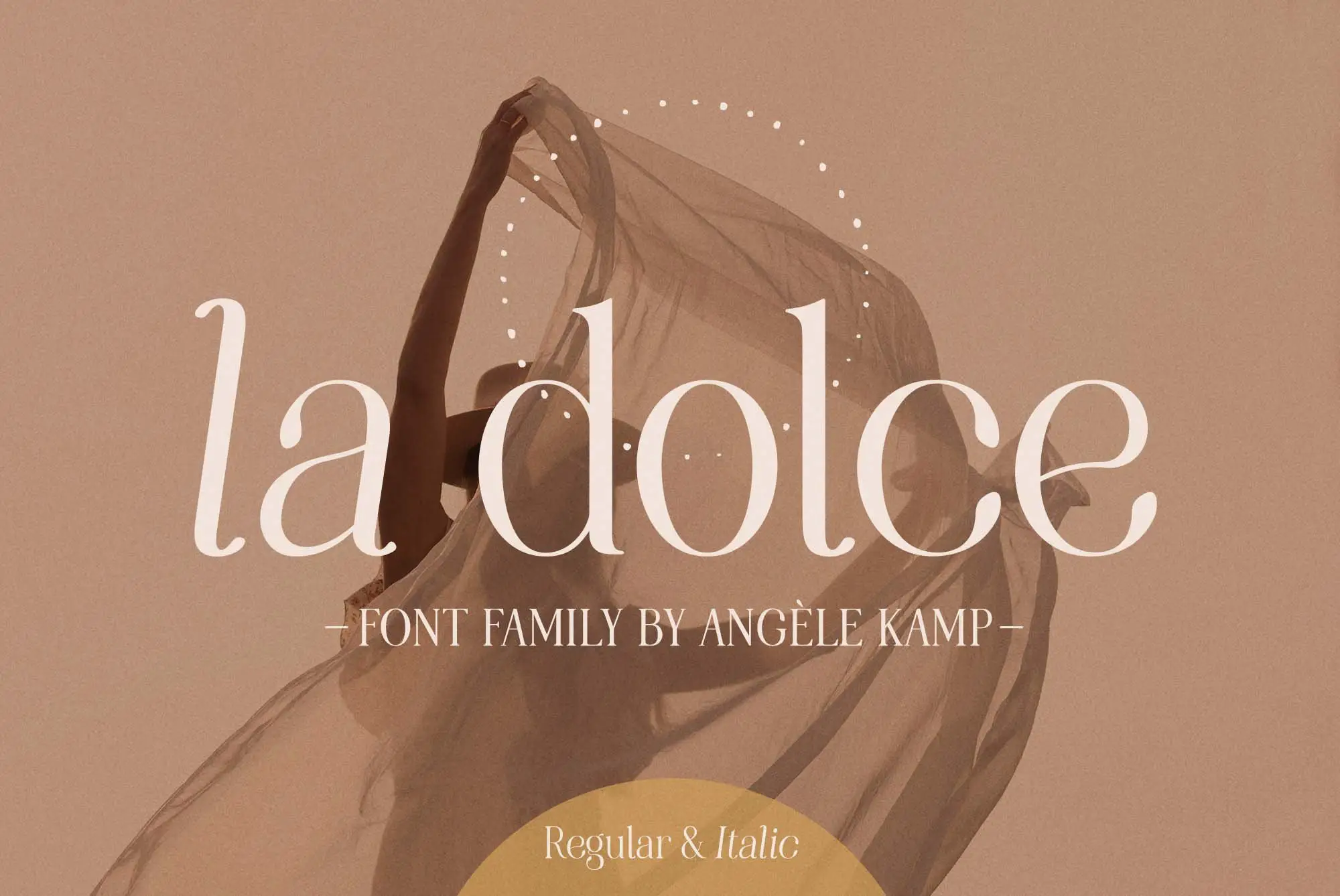
La Dolce は、フェミニンな雰囲気を醸し出す洗練されたセリフ フォント ファミリーです。 優雅さとスタイルを必要とするあらゆるデザインプロジェクトに最適です。
このフォント コレクションには、太字、標準、斜体、太字斜体を含む 4 つの異なるスタイルが含まれており、多用途性と機能性を備えています。
精緻なディテールとエレガントなスタイルが印象的です。 Google Serif フォントは人気の検索語であるため、このフォント ファミリはコレクションに追加するのに最適で、検索結果で目立つユニークなデザインを作成するのに役立ちます。
レイジェンシー
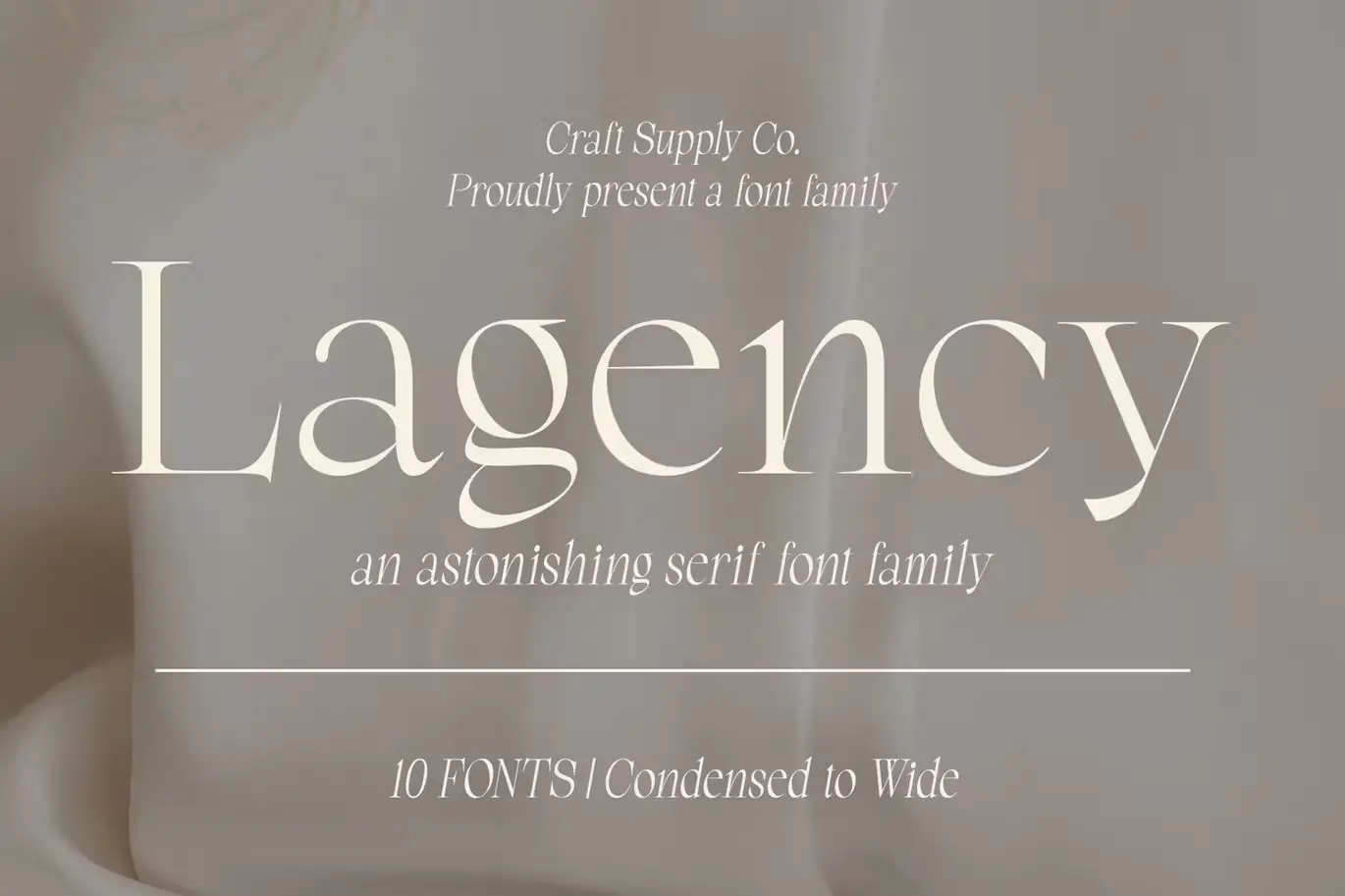
Lagency は多用途で美しいセリフ フォントで、凝縮からワイドまで 10 種類のスタイルがあります。 印刷物、Web、ロゴデザインなど、さまざまな用途に最適です。 フォントの柔軟性の必要性を理解しているグラフィック デザイナーが、愛情を込めて Lagency をデザインしました。
モダンな Serif フォントのきれいな線と印象的なタイポグラフィーは、印刷または Web プロジェクトでの使用に最適です。 大画面でも読みやすい書体を探している場合でも、ロゴやその他のグラフィックスに個性を加える特別なものが必要な場合でも、Lagency は最適な選択肢です。
Lagency では太字フォントが利用できるため、すべてのアプリケーションで独自の外観を実現できます。 どのスタイルを選択しても、このフォントの品質は期待を裏切りません。
セントリオ
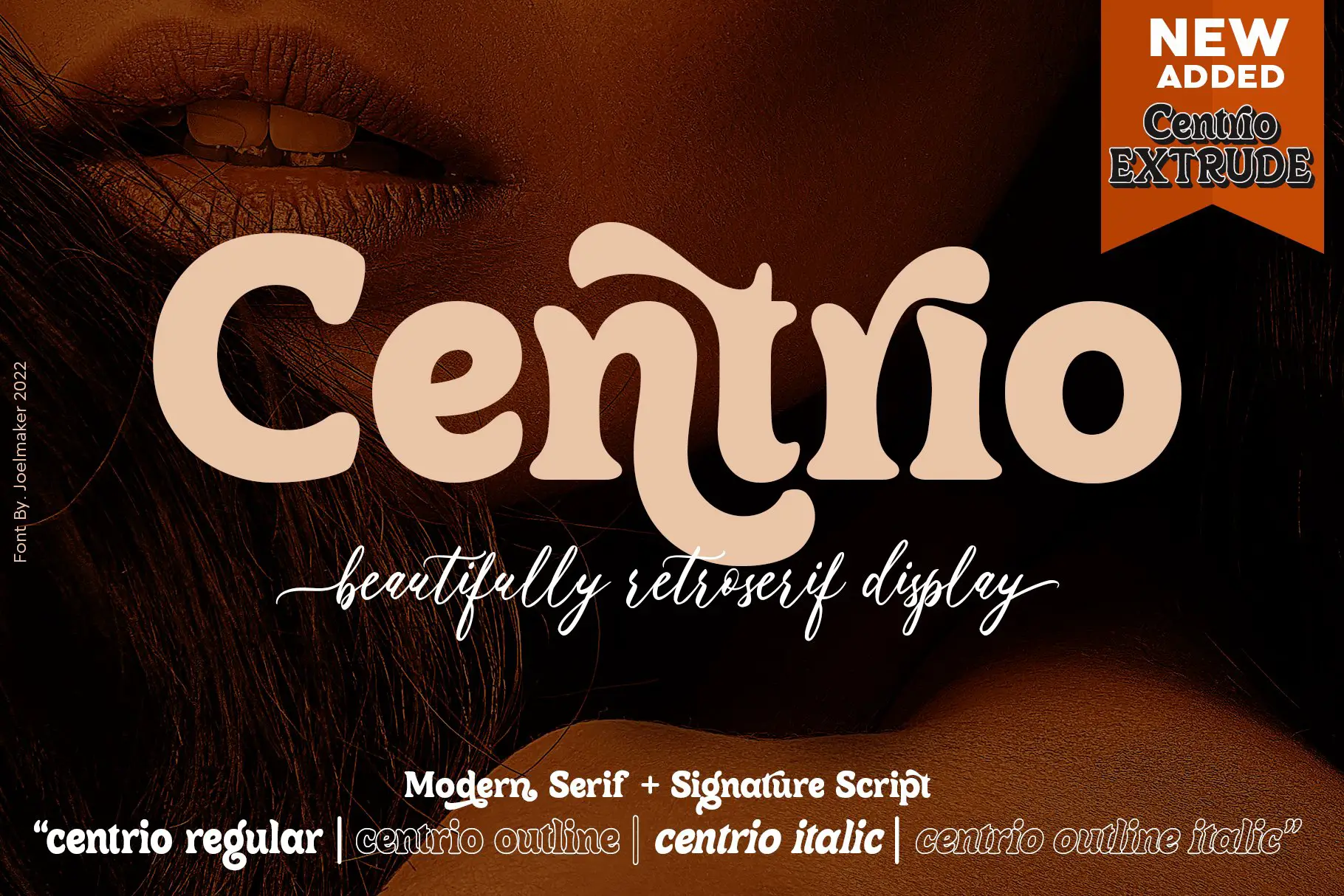
Centrio は、ヴィンテージとモダンなデザインの世界を芸術的なタッチで組み合わせた書体です。 エレガンスとユニークさが完璧に融合しており、センスが必要なあらゆるプロジェクトに最適です。
Centrio の特徴は、合字と渦巻き状の埋め込みの使用であり、これにより確実に主張するモダンなフォントが作成されます。
この書体は、雑誌のタイトル、ポスター、ロゴ、T シャツ、サブタイトル、名刺、雑誌、本の表紙、結婚式の招待状、Instagram ストーリーの投稿、グリーティング カード、引用など、さまざまな目的に使用できます。
トレリス
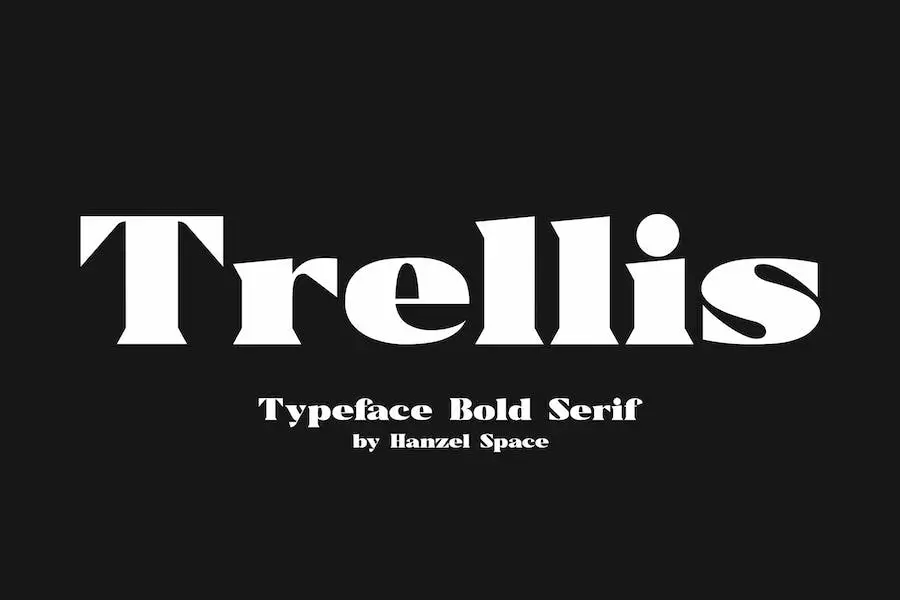
Trellis は、間違いなく目を引く美しい太字のセリフ フォントです。 細いストロークと組み合わせたシャープなセリフのユニークなデザインは、ロゴ、エディトリアル作品、または Web デザインに最適な、見事なミッドセンチュリーの建築的な雰囲気を作り出します。
この OTF フォントには大文字、小文字、数字、句読点が含まれており、さまざまなデザイン プロジェクトに多用途に使用できます。 Web フォントとしても利用できるため、品質を損なうことなくデジタル プラットフォームで使用できます。
レトロでありながらモダンなものをお探しなら、Trellis が最適です。 その大胆さとユニークさは、あなたのプロジェクトを他のプロジェクトよりも際立たせるでしょう。 さらに、その多用途性により、個人使用か商業使用かを問わず、あらゆるデザイン プロジェクトに適しています。
全体として、Trellis は、特にさまざまなデザイン プロジェクトに最適なモダンなセリフ フォントを探している場合に、フォント コレクションに追加するのに最適です。
アビントン
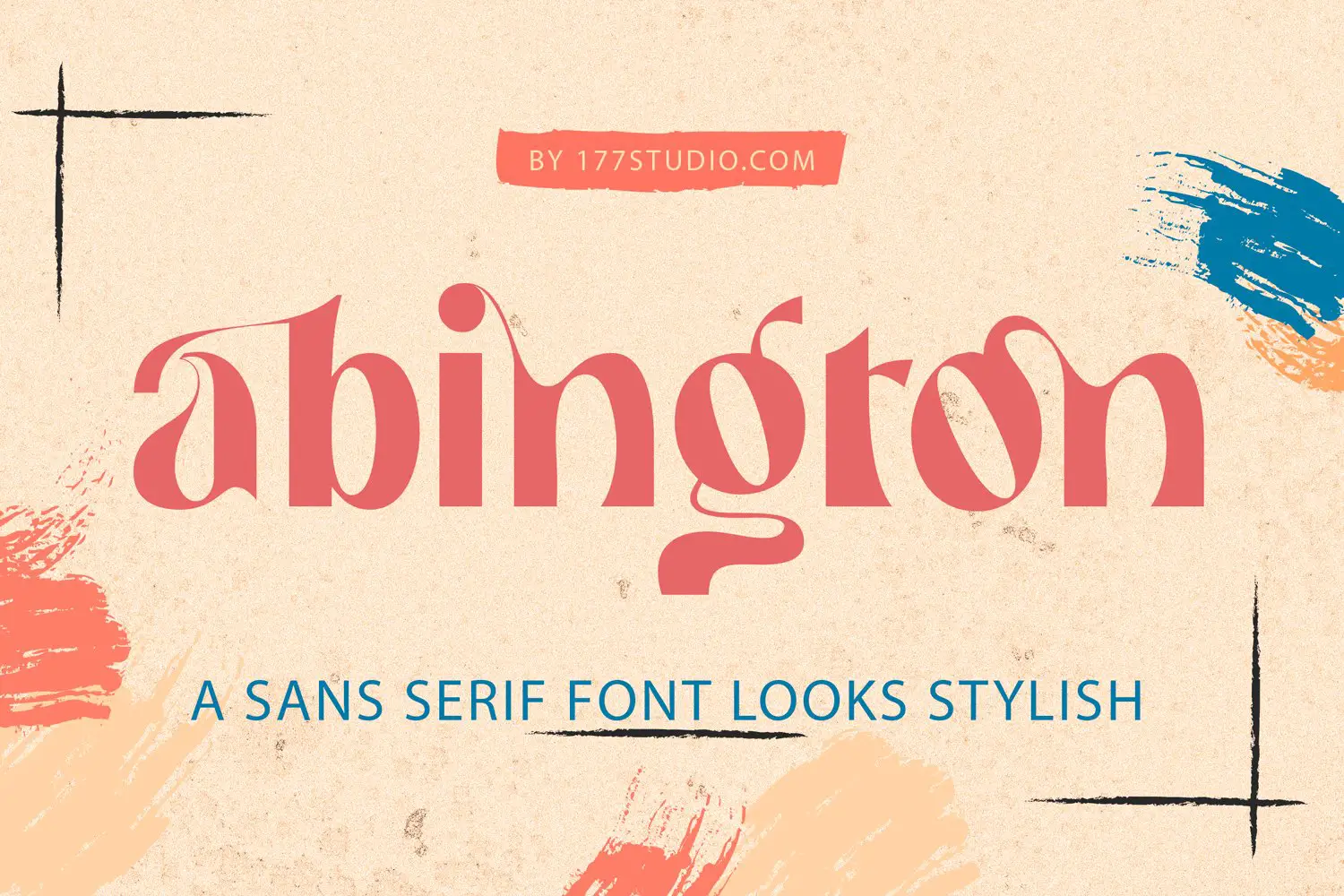
Abington フォントは、デザインにしっかりとした魅力的でスタイリッシュな外観をもたらす、モダンでアンティークなサンセリフ フォントです。
エレガントで洗練された雰囲気を醸し出し、あらゆるプロジェクトに高級感を加えます。 Abington フォントは、ブランディング プロジェクト、ロゴ デザイン、結婚式の招待状、ソーシャル メディアの投稿、広告、製品パッケージ、製品デザイン、ラベル、写真、透かし、文房具など、基本的に手書きのセンスが必要なものすべてに最適です。
Abington フォントには、他のフォントとは一線を画す幅広い機能が備わっています。 まず、その大胆でユニークなデザインは読みやすく、見る人の目を瞬時に捉えます。
次に、セリフ スタイルとスラブ スタイルの両方で利用できるため、ユーザーはデザインする際に柔軟性と多用途性を得ることができます。 第三に、印刷メディアだけでなくデジタルでも見栄えの良いフォントです。 最後に、Abington フォントは商用目的でも使用でき、プロ仕様のフォントを必要とするデザイナーに最適です。
マキシマムビジョナリー
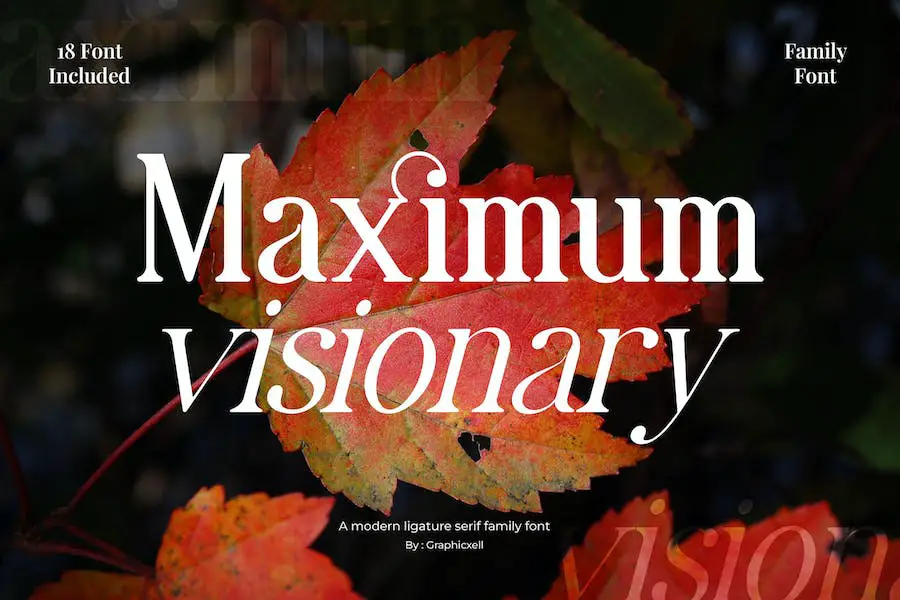
Maximum Visionary は、テンプレート、パンフレット、ビデオ、広告ブランディング、ロゴ、招待状、レイアウト デザイン、エレガントなクラフト、美しさのデザインなど、さまざまなデザイン目的に最適なエレガントなセリフ フォントです。
Maximum Visionary の際立った特徴の 1 つは、そのミニマルなデザインであり、モダンでスタイリッシュなデザインの作成に最適です。
さらに、フォントは PUA でエンコードされているため、追加のデザイン ソフトウェアを必要とせずにすべての文字に完全にアクセスできます。 このフォントには多言語サポートも含まれているため、世界中のデザイナーが使いやすくなっています。
エングレース
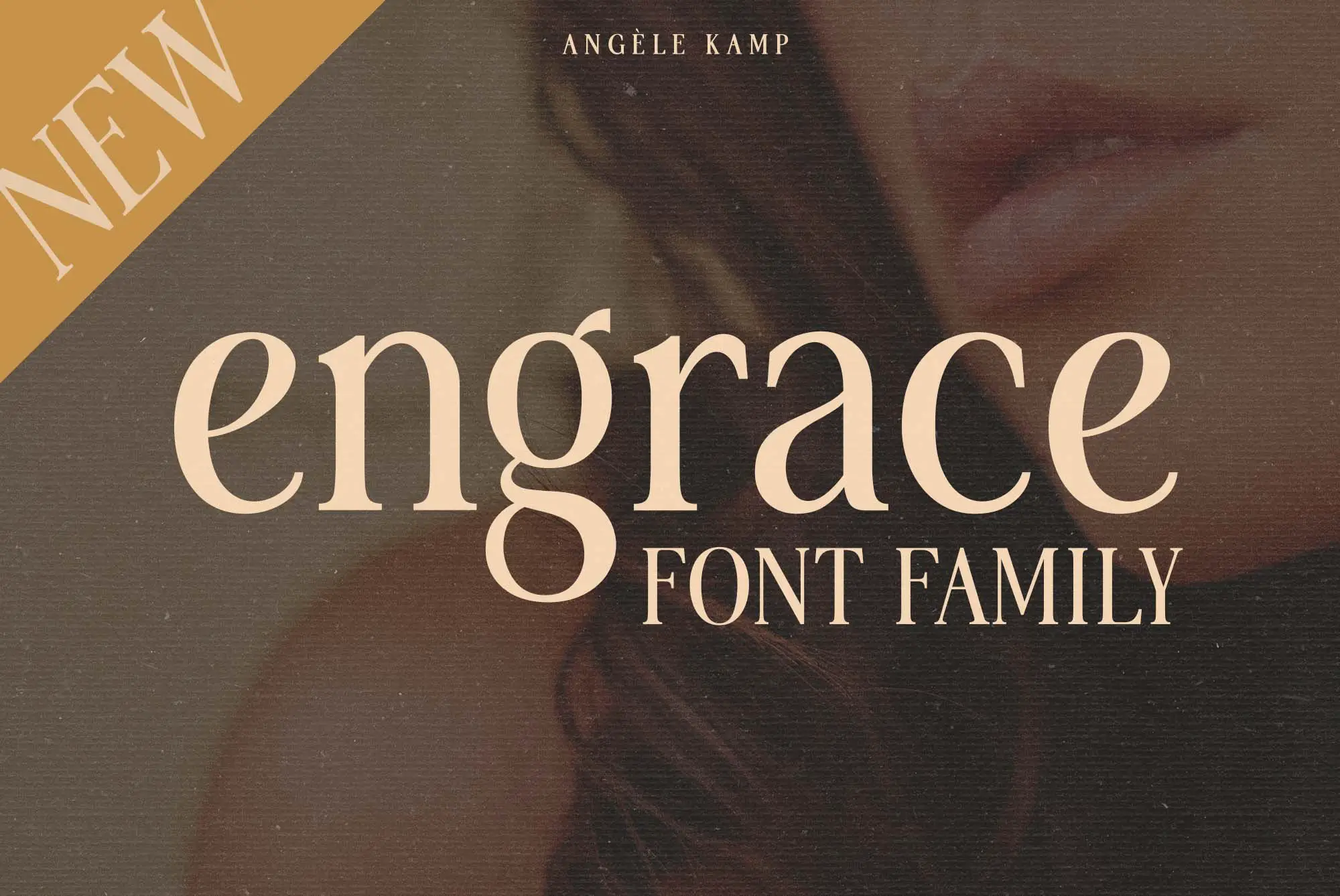
Engrace は、デザインに優雅さとスタイルを加えたい人にとって完璧なセリフ フォント ファミリです。
この多用途の可変フォントは、標準および斜体でライトからボールドまでのウェイトが用意されており、あらゆるプロジェクトに最適です。
その曲線はロマンチックでありながらモダンであり、上品でファッショナブルなデザインを作成したい人にとって優れた選択肢として際立っています。
Engrace の際立った特徴の 1 つは、高級感とハイファッションがすべて 1 つにまとめられていることです。
このフォント ファミリーは多用途であるだけでなく、優雅さと高級感を定義します。 ロゴ、Web サイト、印刷物のいずれをデザインしている場合でも、Engrace を使用すると、あなたのプロジェクトが他よりも目立つようになります。
Engrace は商用利用に最適であるため、プロジェクトに信頼性が高くスタイリッシュなフォントを必要とするデザイナーにとって優れた選択肢となります。 Word 用の Serif フォントを検討している場合にも最適です。
ラメシャ
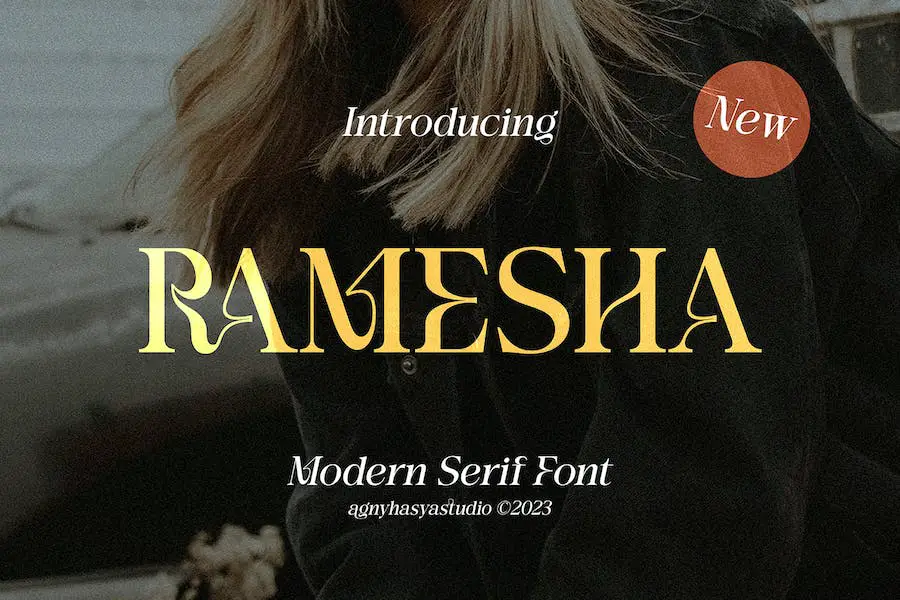
Ramesha は、代替文字や合字などのさまざまなグリフ バリエーションを提供する、モダンでエレガントなセリフ書体フォントです。
この洗練された書体は、洗練された本格的なタイポグラフィ デザインを作成したい、または Canva でセリフ フォントを使用したいデザイナーに最適です。
そのユニークな機能により、Ramesha は市場の他のセリフ フォントよりも際立っています。 ロゴ、ブランディング、広告、製品デザイン、文具、雑誌のデザイン、本/表紙のタイトル デザイン、写真、アートの引用、結婚式のデザイン、ファッション デザイン、特別なイベントなど、さまざまなデザイン プロジェクトに使用できる多用途のフォントです。ラベル、製品パッケージなど。
エスポティカ
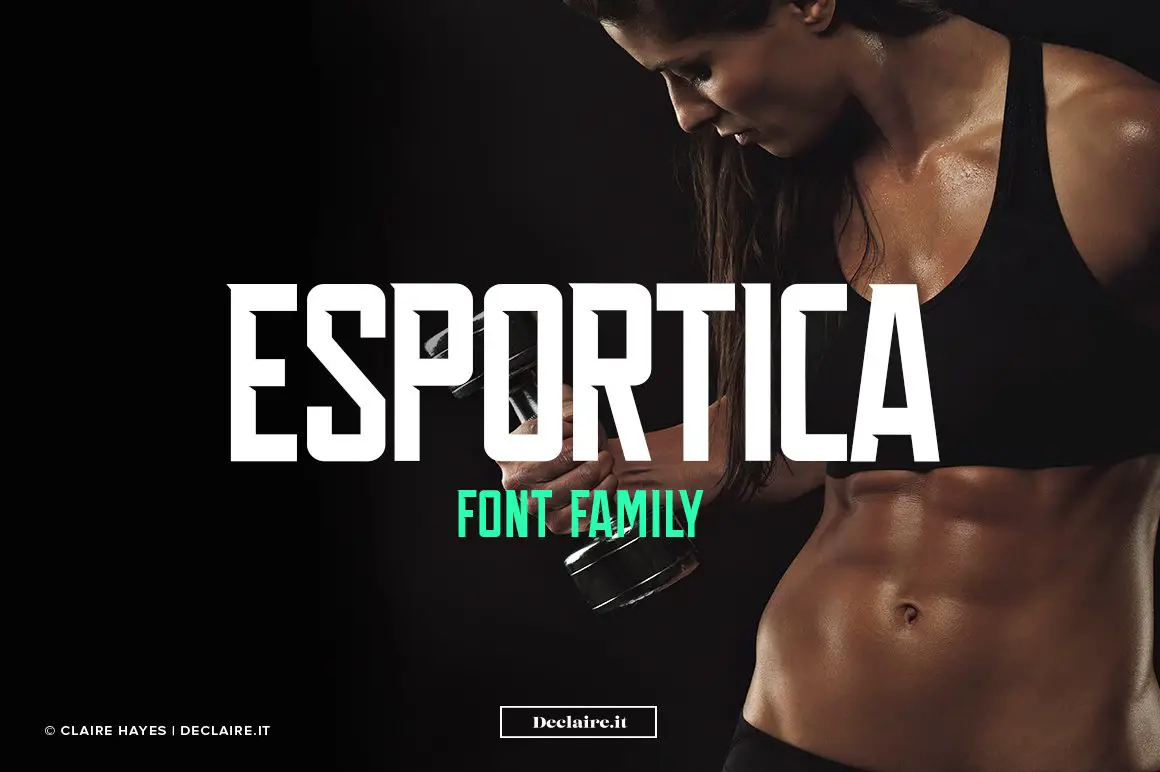
Esportica は、目を引く見出しの作成に最適な最新の表示書体です。
このフォントには、大文字と小文字、句読点、数字を含む 230 の固有のグリフが装備されており、複数の国際言語もサポートされています。 Mac と PC の両方のオペレーティング システムと互換性があります。
デザインを向上させる新しいフォントを探しているなら、Esportica がまさに必要なものかもしれません。 大胆でモダンな外観を提供する現代的なセリフ フォントです。
Esportica の大胆なスラブ セリフは、見出し、ロゴ、ポスター、その他のグラフィック デザイン プロジェクトに最適です。
このフォントのモダンでありながらクラシックな外観は、作品に洗練されたタッチを取り入れたいデザイナーに最適です。
グリル
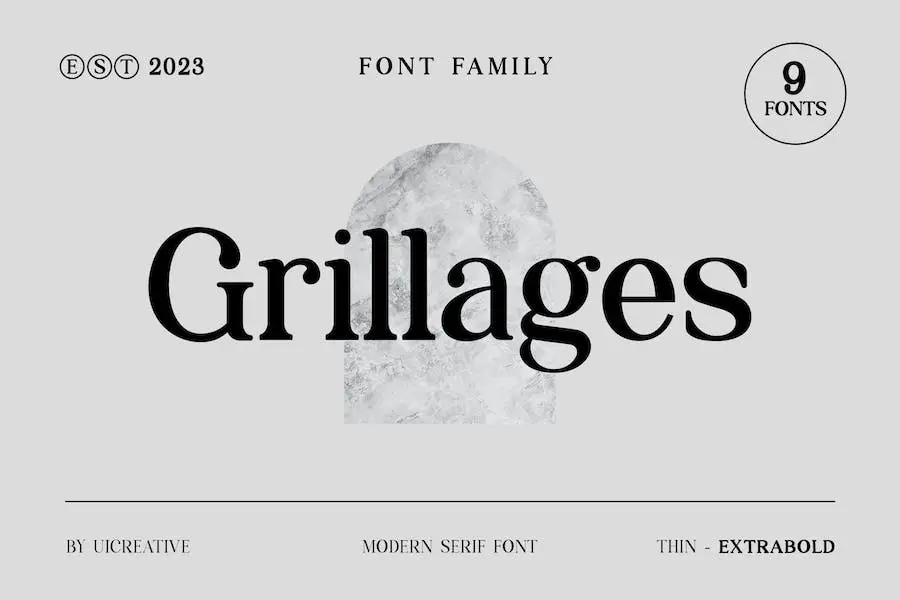
Grirages は、あらゆるプロジェクトに高級感と優雅さを加えるモダンなセリフ フォントです。 そのデザインは女性らしさと男性らしさの両方を兼ね備えており、ロゴ、文房具、本の表紙、タイポグラフィーの引用、さらには衣類のデザインなど、さまざまな用途に最適です。
このフォントは大胆で威厳のある存在感を持っており、ファッション関連のブランディングやエディトリアル表示に最適です。
ただし、グリラージュの多用途性はファッション業界を超えています。 ウェブサイトのヘッダー、パッケージデザイン、その他多くの商用アプリケーションに使用できます。
カサブランカ
Casablanca は、セリフ フォントの洗練されたエキゾチックな魅力と、美しく作られた合字を簡単に融合させた素晴らしいフォントで、エレガントで洗練されたプロジェクトのデザインに最適です。
そのため、不必要なフォントのバリエーションがなく、すっきりとした一貫した外観を求めている人にとっては優れたオプションになります。
全体として、Casablanca はあらゆるプロジェクトに深みと個性を加える必須のセリフ フォントであり、クライアントに好印象を与えたいプロのデザイナーにとって頼りになる選択肢となっています。
アディントンCF
Addington CF は、印象的な文字と細部へのこだわりを備えた優れたセリフ フォントです。 汎用性が高く実用性の高い、信頼と職人のような書体です。
結論
要約すると、デザイン プロジェクトにプロフェッショナルでエレガントな雰囲気を加えることができる、最高の 36 個のセリフ フォントを取り上げました。 本の表紙、Web サイトのヘッダー、ロゴなどをデザインする場合、これらのフォントは必ず印象に残ります。